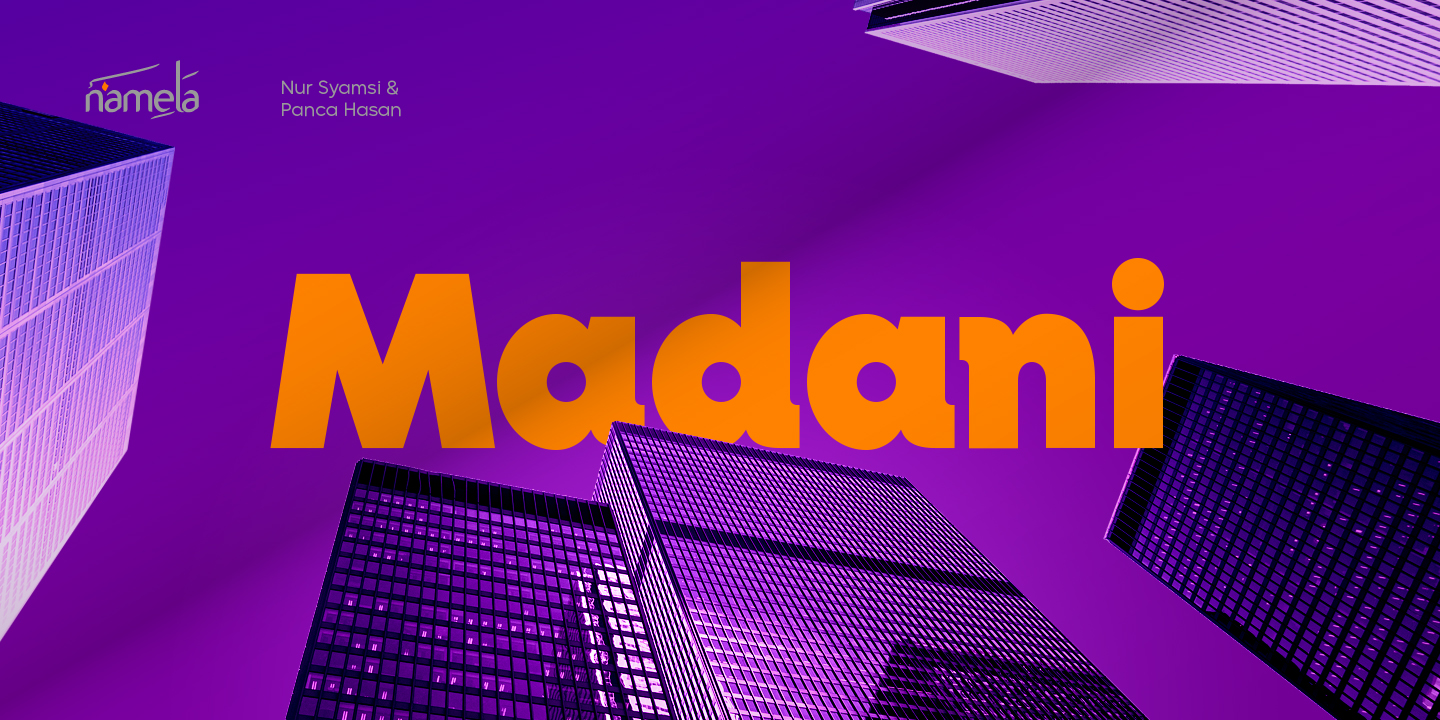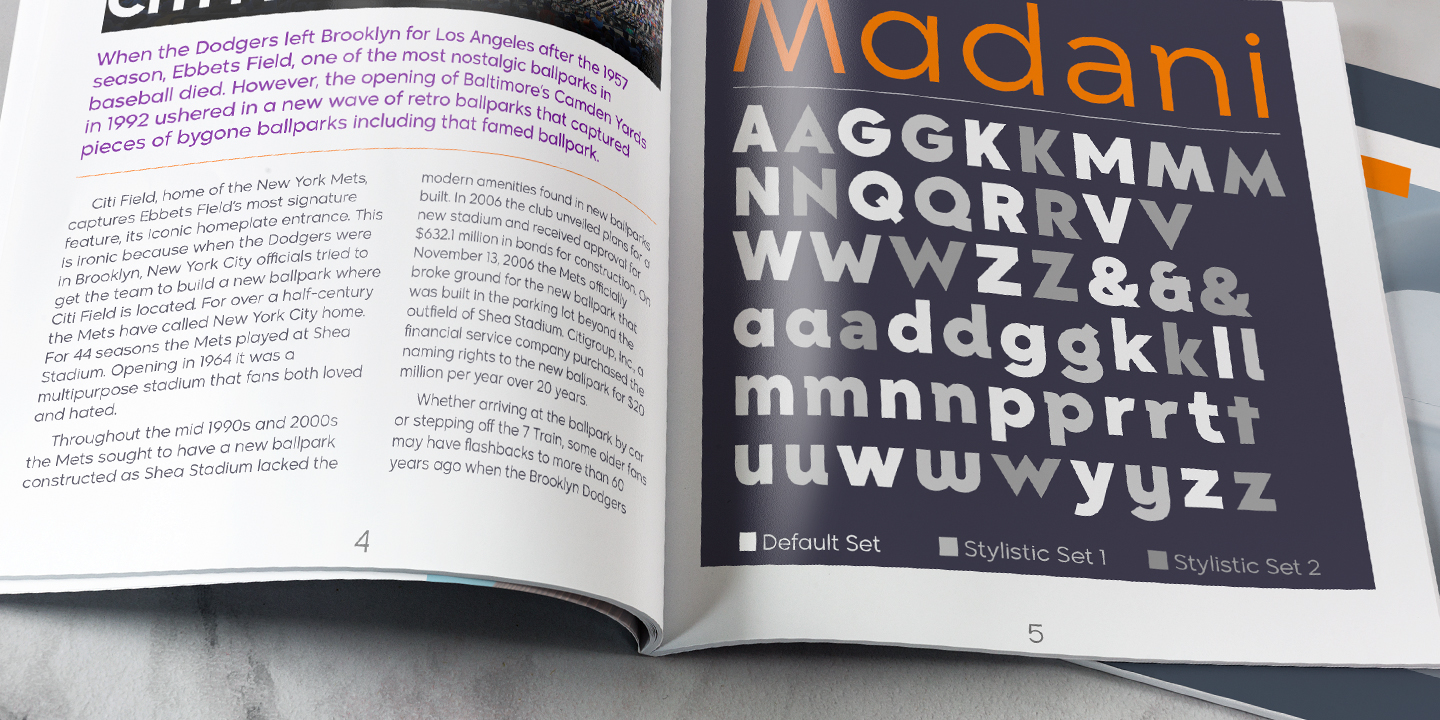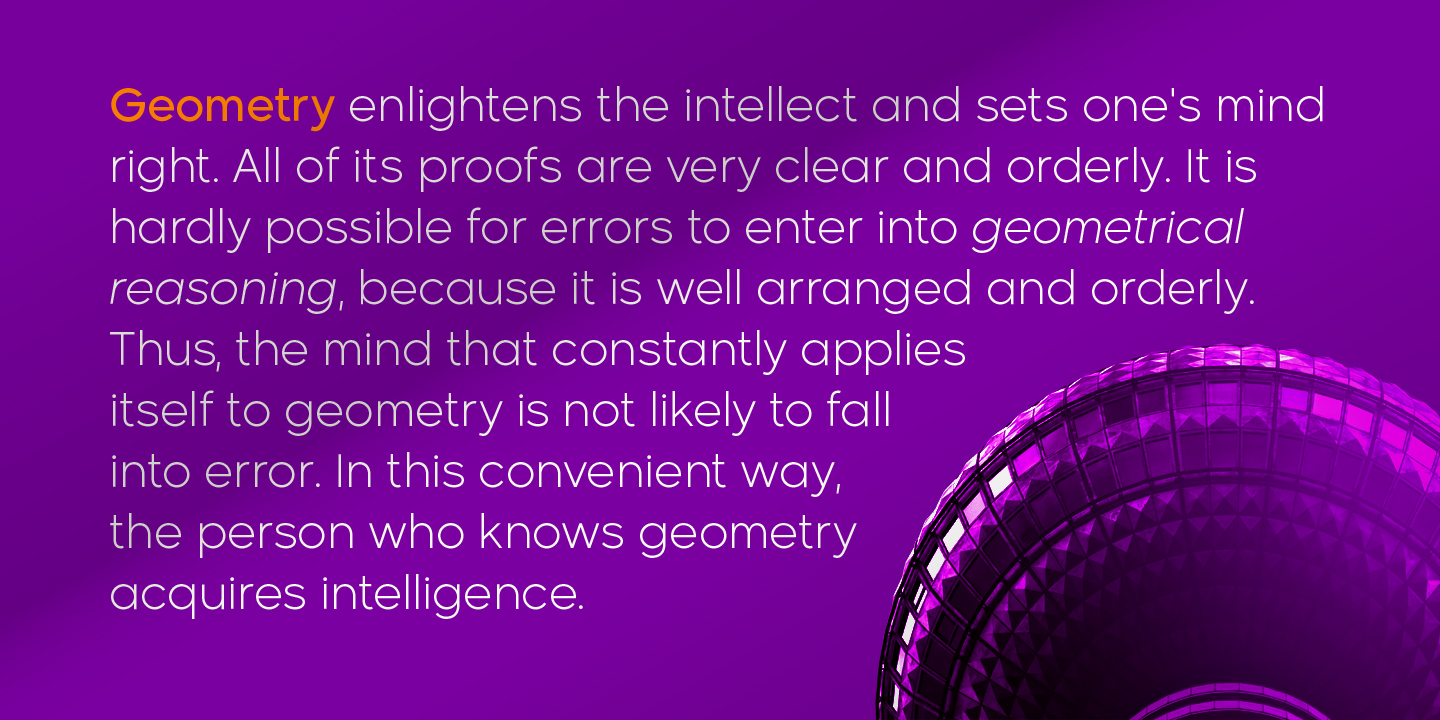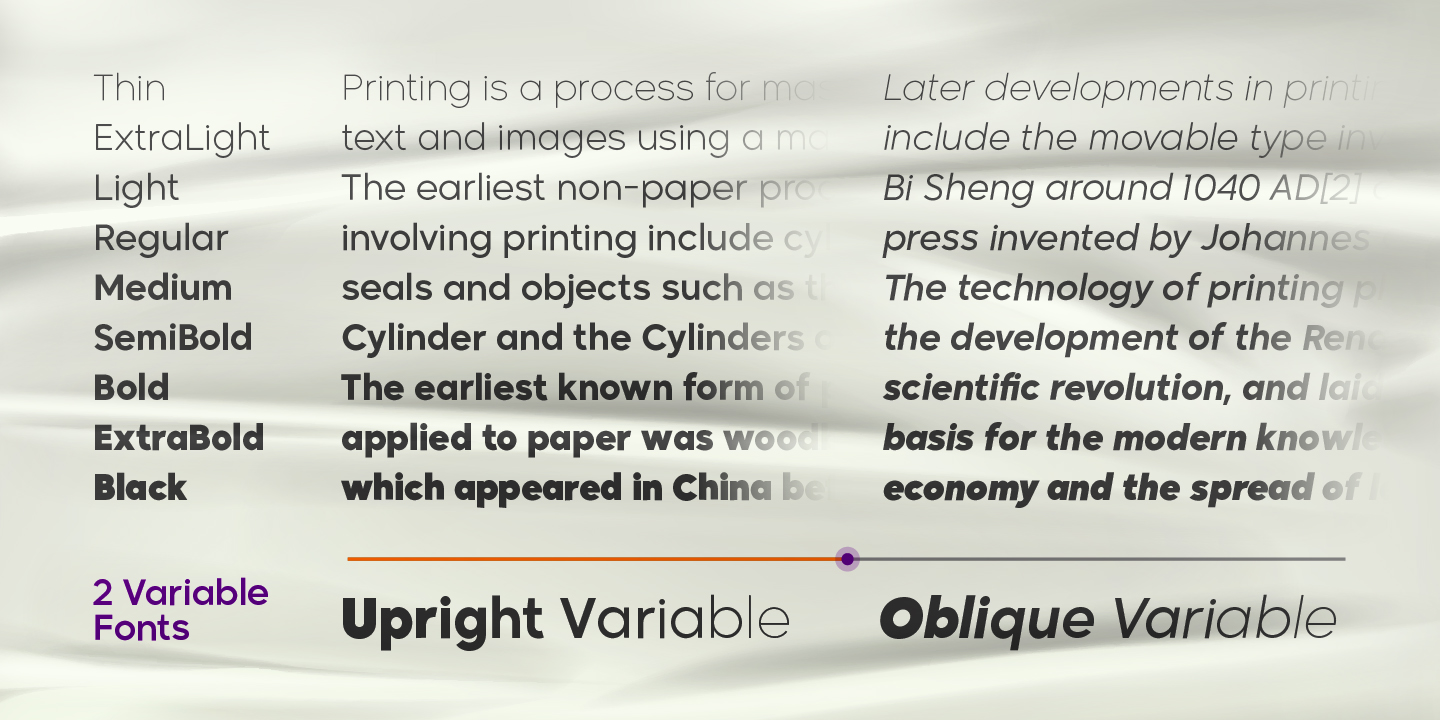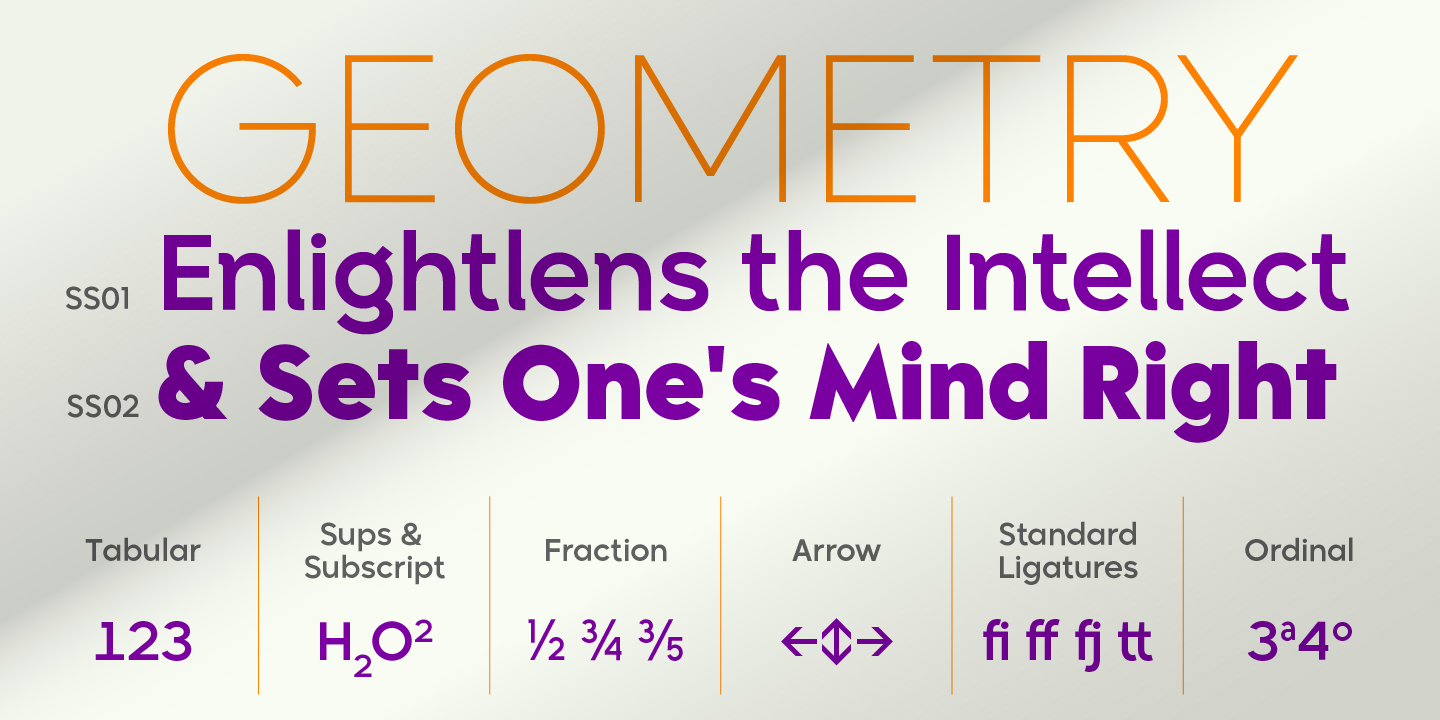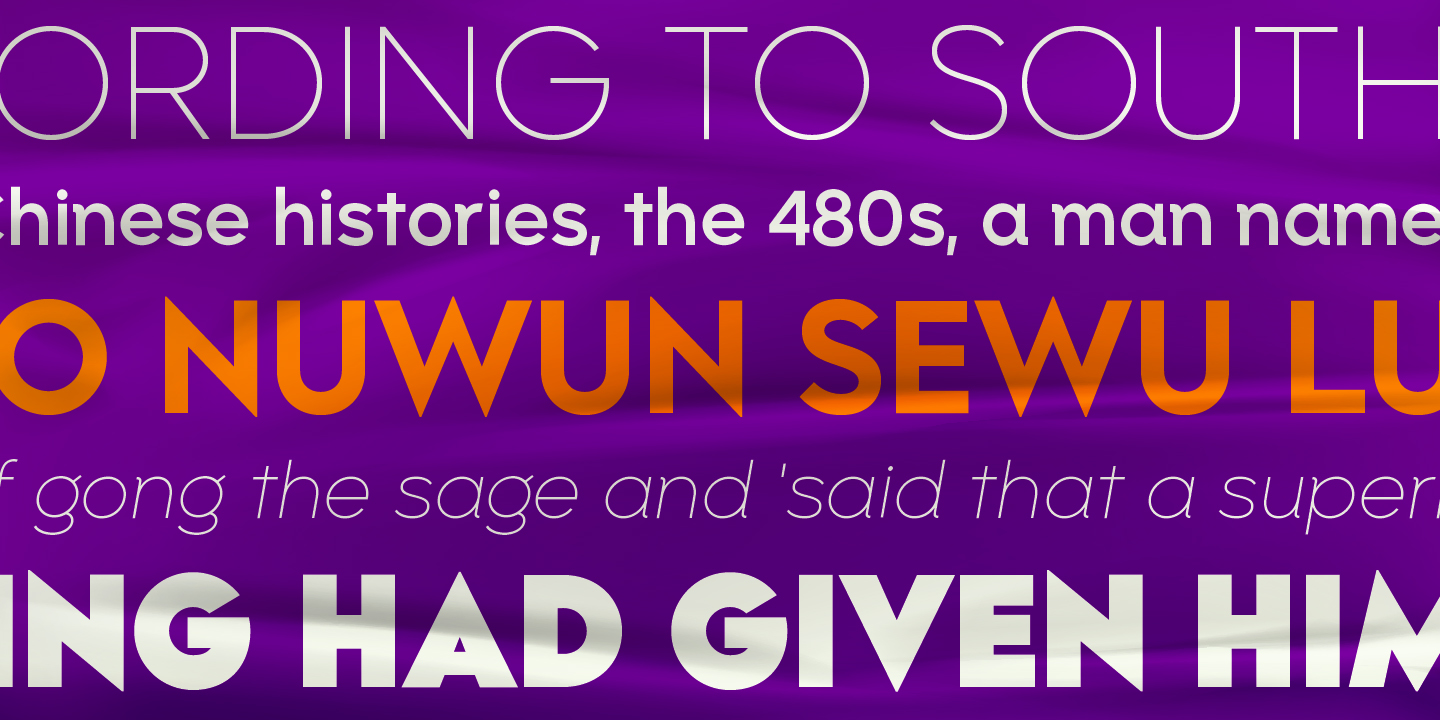
Madani là một sans serif hình học bao gồm 9 weight khác nhau, từ Thin đến Black và phù hợp với Oblique. Với tùy chọn ký tự, thêm các dấu vào một số glyph. Đây là bộ font khá ấn tượng và phù hợp cho mọi thiết kế của bạn